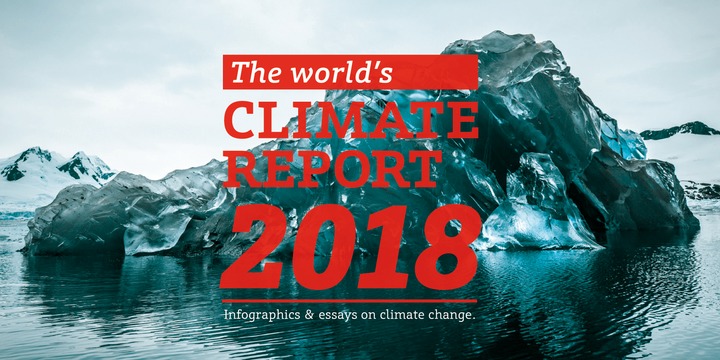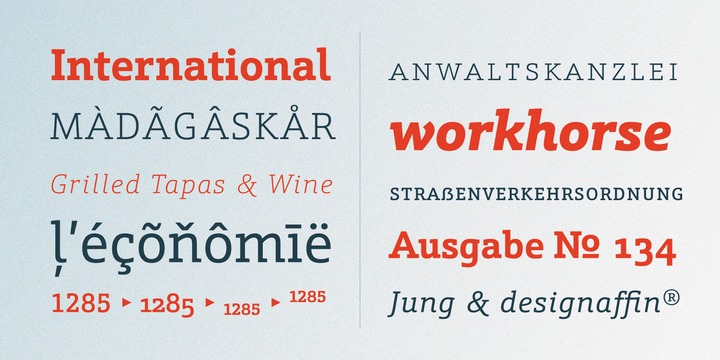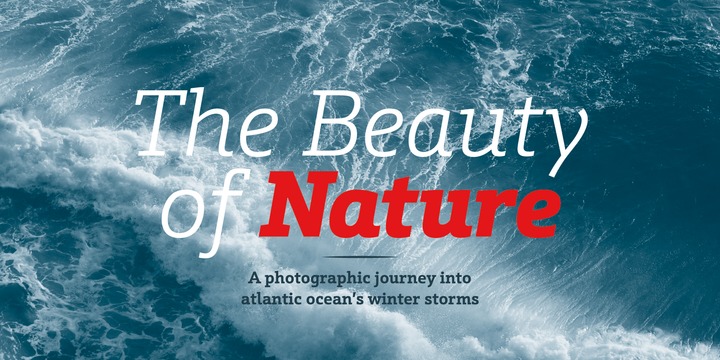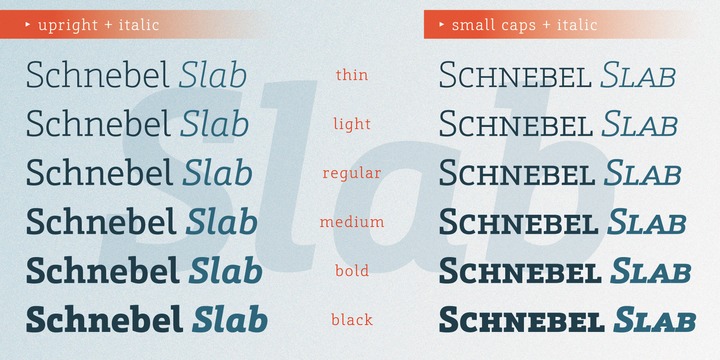
Eine erfrischend klare Antiqua Schnebel Slab ist eine erfrischend klare und starke Interpretation einer zeitgemäßen Antiqua mit wenig Kontrast und kräftigen Serifen, die neben einer hervorragenden Lesbarkeit in kleinen Graden auch den notwendigen Ausdruck vermittelt, wenn sie als Headline verwendet wird.
Die speziell dazu gezeichneten Italic-Schnitte ergänzen ein harmonisches Gesamtbild, das durch seine Ästhetik nie an Spannung verliert.
Der sorgfältige Ausbau mit Ligaturen und Kapitälchen, Proportional- und Mediäval-Ziffern bietet alle Möglichkeiten für einen gepflegten Satz und die große Anzahl von je 6 Fettegraden lässt dem Gestaltungspiel Raum für unterschiedliche Kombinationen.
Dazu tragen auch die zusätzlichen Condensed und Expanded-Varianten bei, von denen jede für sich spezielle Eigenschaften hat und ihre je eigene Anmutung entfaltet.
More Schnebel Slab Pro ist die neueste Veröffentlichung der URW Type Foundry.
The italics, drawn specifically for this purpose, contribute to a harmonious picture, which never loses creative tension, thanks to its aesthetics.
The careful addition of ligatures, small caps, and proportional and old-style figures allows for well-proportioned typesetting.
The condensed and expanded variants, which also come in 6 weights each, offer plenty of freedom to design with numerous combinations.